Tổng hợp 15 font chữ viết tay Việt hóa đẹp, dễ dùng cho thiệp cưới, logo và thiết kế. Hướng dẫn chọn, cài đặt và sử dụng hiệu quả.
Nếu bạn đang tìm font chữ viết tay Việt hóa đẹp, hiển thị chuẩn tiếng Việt và dùng được ngay cho thiết kế, thì danh sách dưới đây sẽ giúp bạn chọn nhanh hơn rất nhiều. Thay vì phải thử từng font rồi gặp lỗi dấu hoặc khó sử dụng, mình đã chọn lọc sẵn 15 font viết tay có đường nét rõ ràng, dễ ứng dụng và phù hợp với nhiều mục đích như thiệp cưới, logo hay nội dung mạng xã hội.
Font chữ viết tay Việt hóa là gì? Vì sao ngày càng được ưa chuộng?
Font chữ viết tay (handwritten fonts) là kiểu chữ mô phỏng nét viết thật của con người – có thể mềm mại, bay bổng hoặc cá tính, phóng khoáng. Khi được Việt hóa, font sẽ hiển thị đầy đủ dấu (ă, â, ê, ơ, ư…) mà không lỗi ký tự.
Vì sao được dùng nhiều?
- Tạo cảm giác gần gũi, tự nhiên, khác với font máy móc.
- Dễ truyền tải cảm xúc (dịu dàng, đáng yêu, sang trọng…).
- Phù hợp với nhiều ngữ cảnh: thiệp cưới, logo cá nhân, poster, story Facebook/Instagram
- Nói đơn giản: cùng một câu chữ, dùng font viết tay “đúng gu” sẽ khiến thiết kế có hồn hơn hẳn.
Tiêu chí chọn font chữ viết tay đẹp và dễ sử dụng
Để chọn được font chữ viết tay phù hợp, bạn nên ưu tiên các tiêu chí dưới đây. Đây cũng là những yếu tố quan trọng giúp font hiển thị đẹp và dễ ứng dụng trong thiết kế thực tế.
Hỗ trợ tiếng Việt (Unicode chuẩn)
Font cần hiển thị đầy đủ dấu tiếng Việt để tránh lỗi khi gõ nội dung.
Điều này đặc biệt quan trọng khi dùng cho thiết kế in ấn, banner hoặc nội dung chính thức.
Độ dễ đọc
Một font đẹp nhưng khó đọc sẽ làm giảm hiệu quả thiết kế.
Bạn nên chọn font có độ rõ ràng tốt, đặc biệt khi dùng cho tiêu đề, poster hoặc nội dung hiển thị nhiều chữ.
Phù hợp với mục đích sử dụng
Mỗi loại thiết kế sẽ phù hợp với một kiểu font khác nhau:
- Logo: nên chọn font gọn gàng, tinh tế
- Thiệp cưới: ưu tiên nét mềm mại, bay bổng
- Mạng xã hội: font dễ thương, gần gũi, dễ nhìn
Việc chọn đúng font theo mục đích sẽ giúp thiết kế trông chuyên nghiệp hơn.
Phong cách thẩm mỹ rõ ràng
Font nên có phong cách cụ thể như dễ thương, sang trọng hoặc cá tính, tránh những kiểu chữ không rõ định hướng.
Điều này giúp bạn dễ phối hợp font và giữ được sự thống nhất trong thiết kế.
Gợi ý: Nếu bạn chưa chắc nên chọn font nào, hãy ưu tiên những font đã được Việt hóa và tối ưu sẵn để đảm bảo hiển thị ổn định khi sử dụng.
Top 15 font chữ viết tay Việt hóa đẹp nhất 2026 (có link tải)
1. TH Quadrien Script – Thanh lịch, bay bổng
Font mang phong cách viết tay mềm mại với các nét uốn lượn nhẹ, tạo cảm giác liền mạch và tự nhiên khi nhìn vào. Chữ có độ thanh thoát, phần đuôi được kéo dài vừa phải giúp tổng thể không bị cứng. Điểm dễ nhận thấy là các ký tự kết nối khá mượt, nên khi dùng cho tiêu đề hoặc câu ngắn sẽ rất nổi bật. Font này phù hợp cho thiệp cưới, caption hoặc thiết kế mang phong cách nhẹ nhàng, tinh tế. Phù hợp dùng cho tiêu đề, không nên dùng cho đoạn văn dài vì nhiều nét nối.
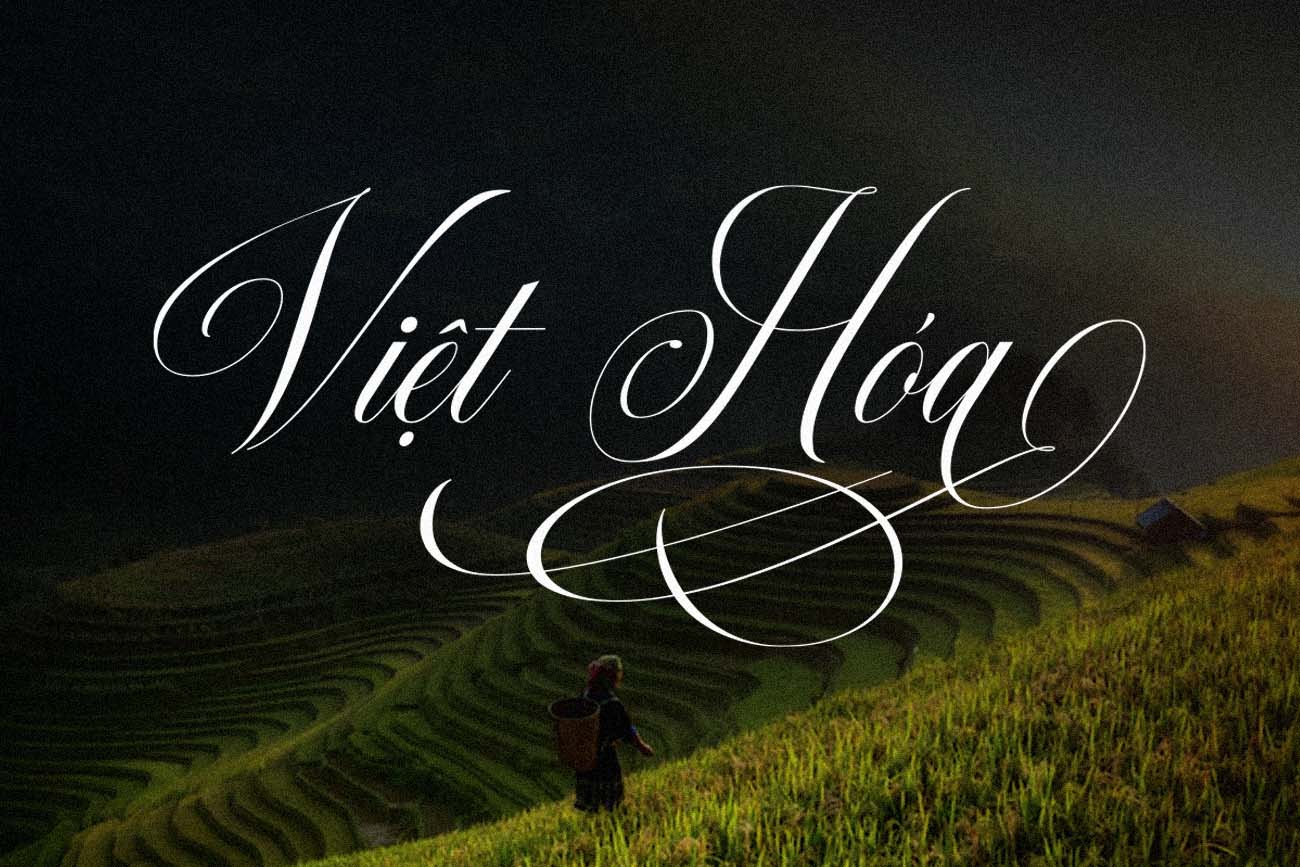
2. TH Newly Bridal – Dịu dàng, lãng mạn
Kiểu chữ có dáng tròn, mềm và hơi nghiêng nhẹ, tạo cảm giác gần gũi và dễ đọc. Các nét được bo đều, không quá sắc nên mang lại sự dễ chịu khi nhìn lâu. Phần đuôi chữ kéo nhẹ tạo điểm nhấn tinh tế mà không bị rối. Tổng thể font mang hơi hướng nữ tính, rất phù hợp cho thiệp cưới, lời chúc hoặc các thiết kế mang màu sắc tình cảm, nhẹ nhàng.
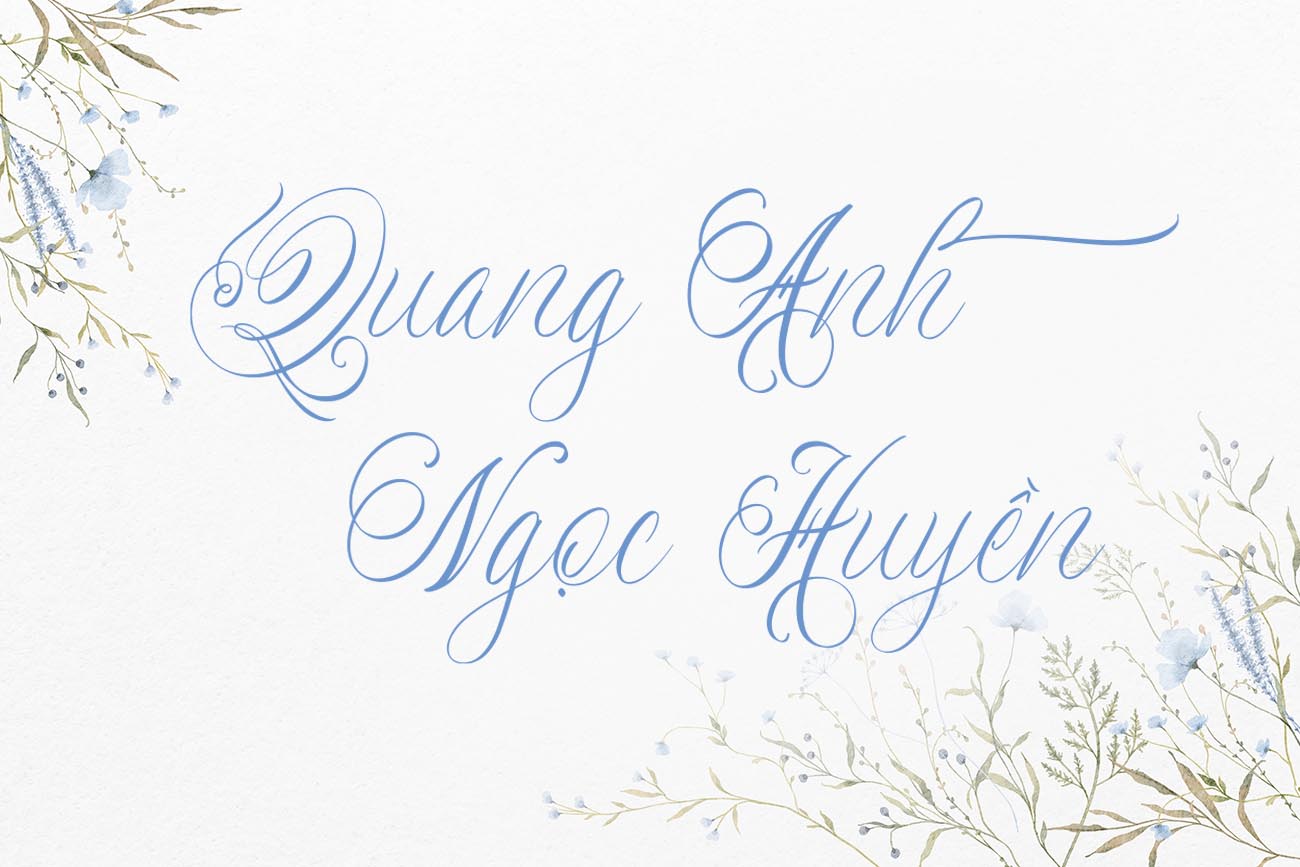
3. TH Berseka – Nghệ thuật, uyển chuyển
Font nổi bật với những đường cong mềm và các chi tiết lượn lớn tạo cảm giác bay bổng. Mỗi ký tự đều có điểm nhấn riêng, đặc biệt ở phần chữ hoa với nét kéo dài rất đẹp. Sự chuyển đổi giữa nét mảnh và nét dày giúp chữ trông sinh động hơn. Kiểu chữ này phù hợp cho tiêu đề trang trí, thiệp cưới hoặc các thiết kế cần tạo ấn tượng ngay từ cái nhìn đầu tiên.
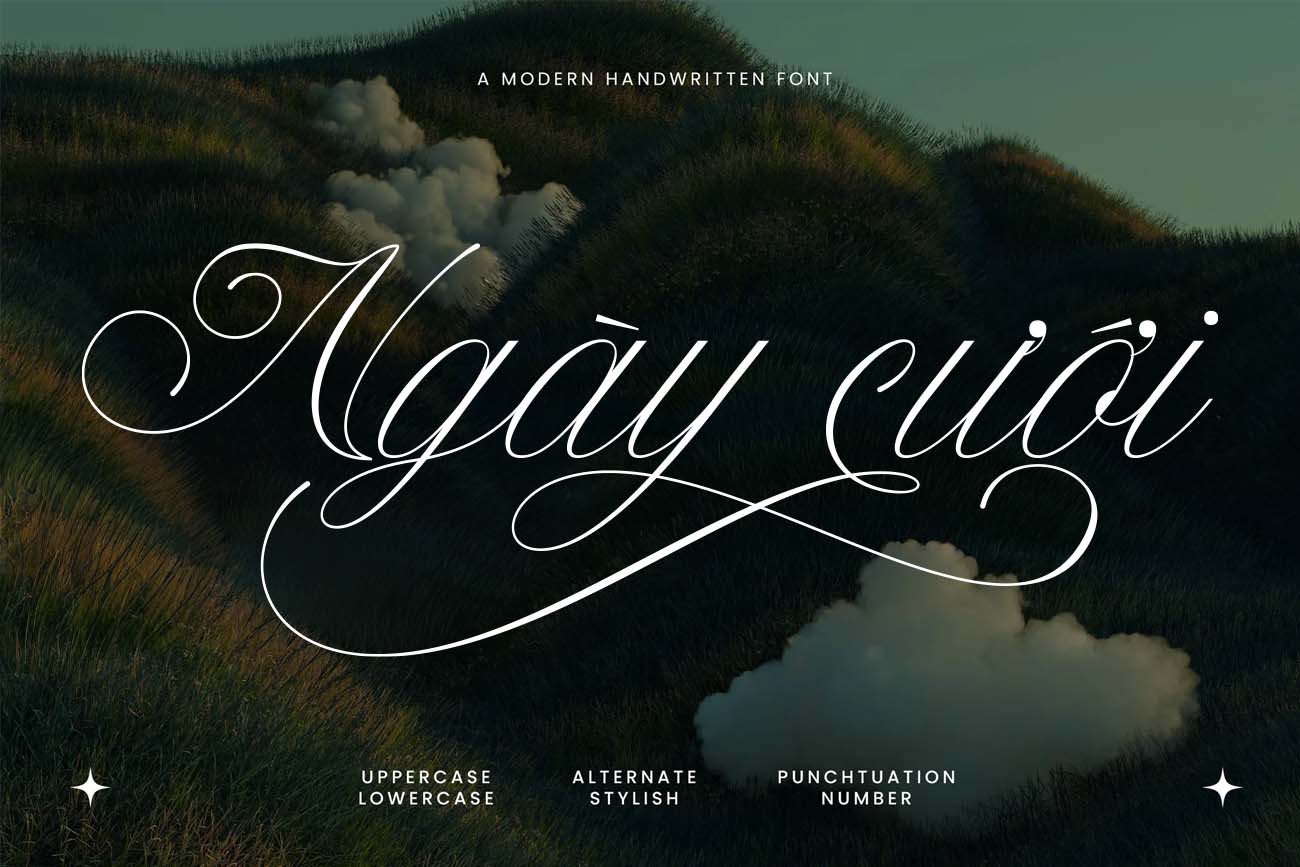
4. TH Jonathan Stattera – Sang trọng, tinh tế
Font mang phong cách chữ ký với các nét liền mạch và thanh thoát. Đường chữ kéo dài tự nhiên, không quá cầu kỳ nhưng vẫn tạo được điểm nhấn. Kiểu dáng chữ hơi nghiêng, tạo cảm giác như chữ ký thật, rất phù hợp với các thiết kế cá nhân hóa. Nhìn tổng thể, font mang lại cảm giác gọn gàng, tinh tế và dễ kết hợp với các kiểu chữ khác trong cùng bố cục.
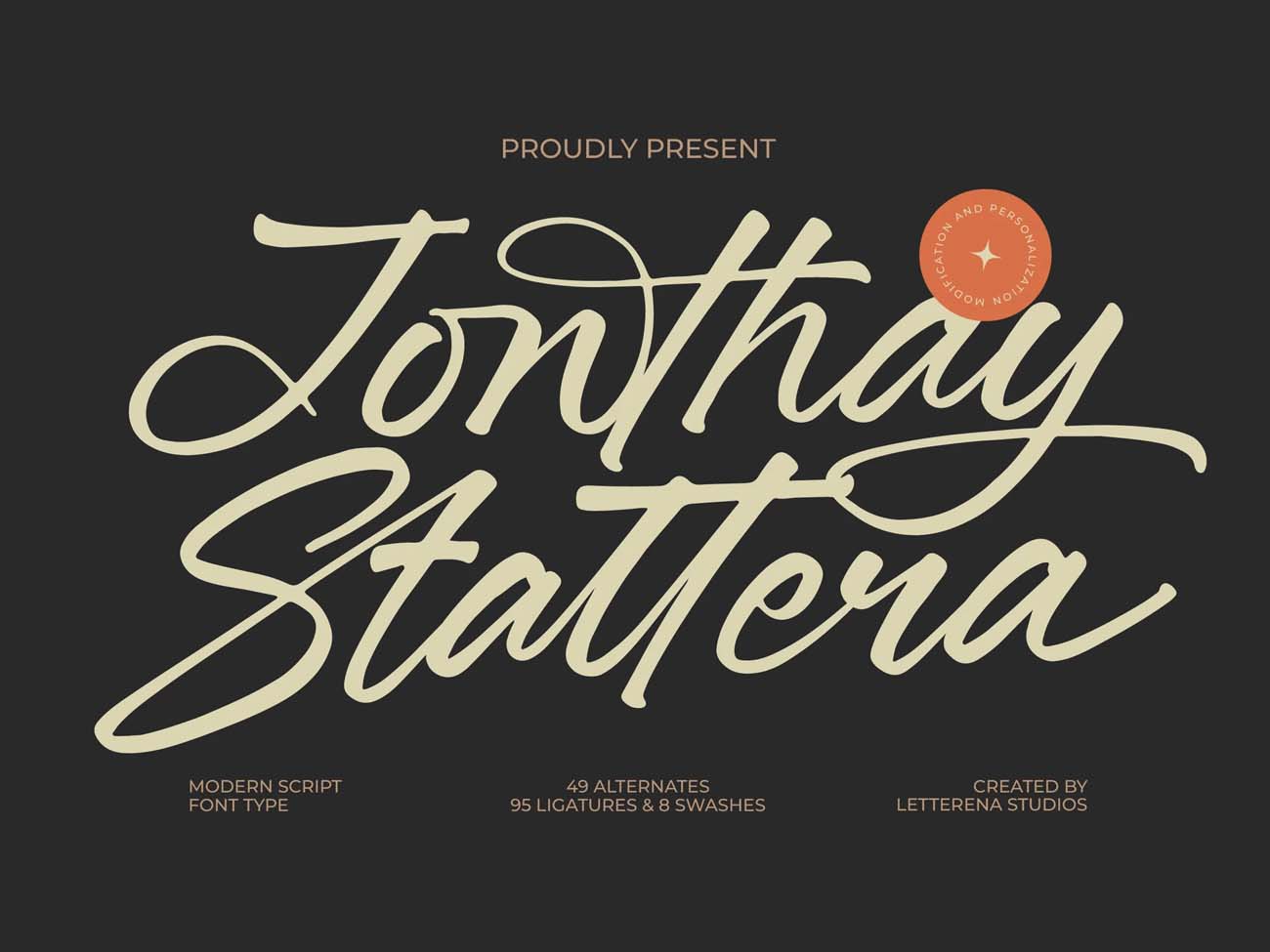
5. TH Ganetha – Mềm mại, thanh thoát
Ganetha có nét chữ nhẹ, uốn cong đều và khá cân đối. Các ký tự được thiết kế không quá phức tạp, giúp dễ sử dụng trong nhiều tình huống. Nét chữ không quá dày nên tạo cảm giác thanh thoát, phù hợp với các thiết kế cần sự nhẹ nhàng. Khi dùng cho tiêu đề hoặc thiệp, font này mang lại cảm giác tinh tế, không bị rối mắt.
📁 Tải xuống font chữ TH Ganetha
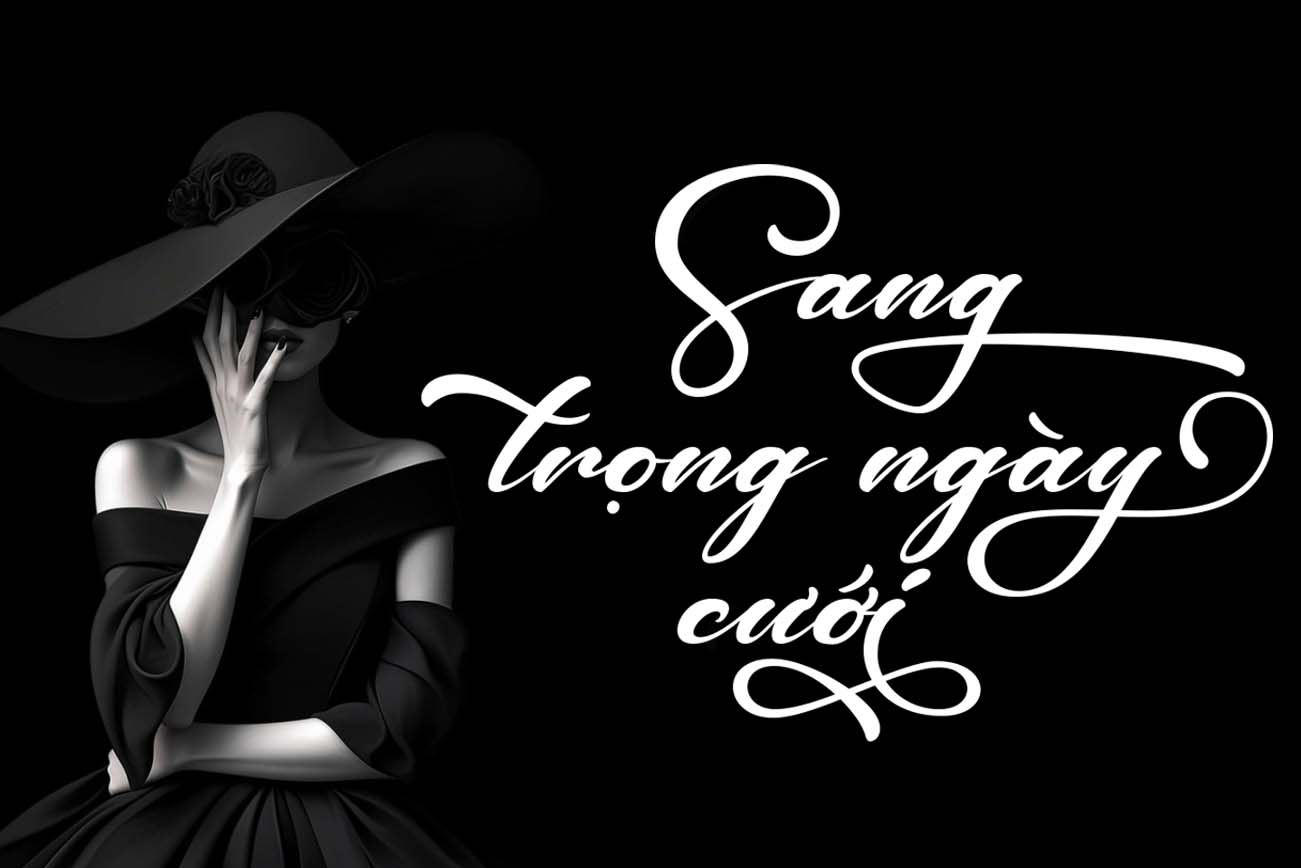
6. TH Bramostia – Cá tính, nổi bật
Font này có nét chữ mạnh, dứt khoát và rõ ràng. Các đường cong được xử lý gọn, tạo cảm giác chắc chắn hơn so với các font mềm mại khác. Dù vẫn giữ phong cách viết tay, nhưng Bramostia thiên về sự cá tính, phù hợp với những thiết kế cần điểm nhấn rõ ràng. Kiểu chữ này rất hợp dùng cho tiêu đề hoặc logo mang phong cách hiện đại.
📁 Tải xuống font chữ TH Bramostia
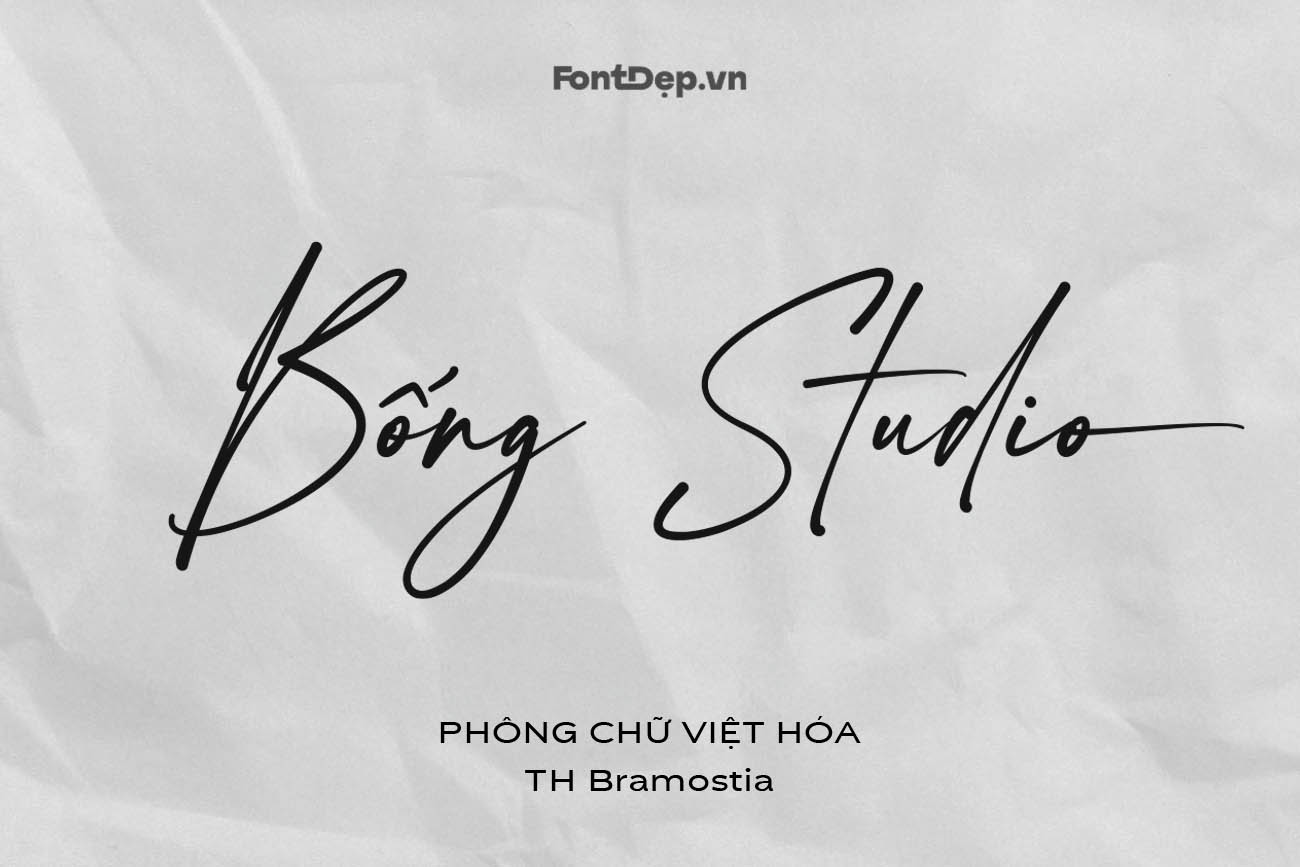
7. TH Kinetic Motion – Mạnh mẽ, hiện đại
Kinetic Motion mang đậm phong cách brush với các nét vẽ dày và có độ chuyển động rõ. Chữ trông như được viết bằng cọ, tạo cảm giác rất sống động. Các nét không đều nhau hoàn toàn, giúp tăng tính tự nhiên. Font này phù hợp với thiết kế quảng cáo, poster hoặc những nội dung cần tạo ấn tượng mạnh ngay từ cái nhìn đầu tiên.
📁 Tải xuống font chữ TH Kinetic Motion
![[Tải Về] Font Brush TH Kinetic Motion Việt Hóa – Nét Cọ Mạnh Mẽ & Hiện Đại](https://fontdep.vn/storage/font-images/font%20chu%20brush%20TH%20Kinetic%20Motion%20viet%20hoa%20anh%201-20250703-130122.jpg)
8. TH Viettay 7 – Phóng khoáng, linh hoạt
Font có nét uốn lượn rõ ràng, mang cảm giác thoải mái và tự nhiên. Các ký tự được thiết kế không quá khuôn mẫu, tạo nên sự mềm mại và linh hoạt. Nét chữ có độ dày vừa phải, đủ để nổi bật mà không gây nặng mắt. Kiểu chữ này dễ dùng trong nhiều thiết kế khác nhau, từ banner đến nội dung mạng xã hội.
📁 Tải xuống font chữ TH Viettay 7
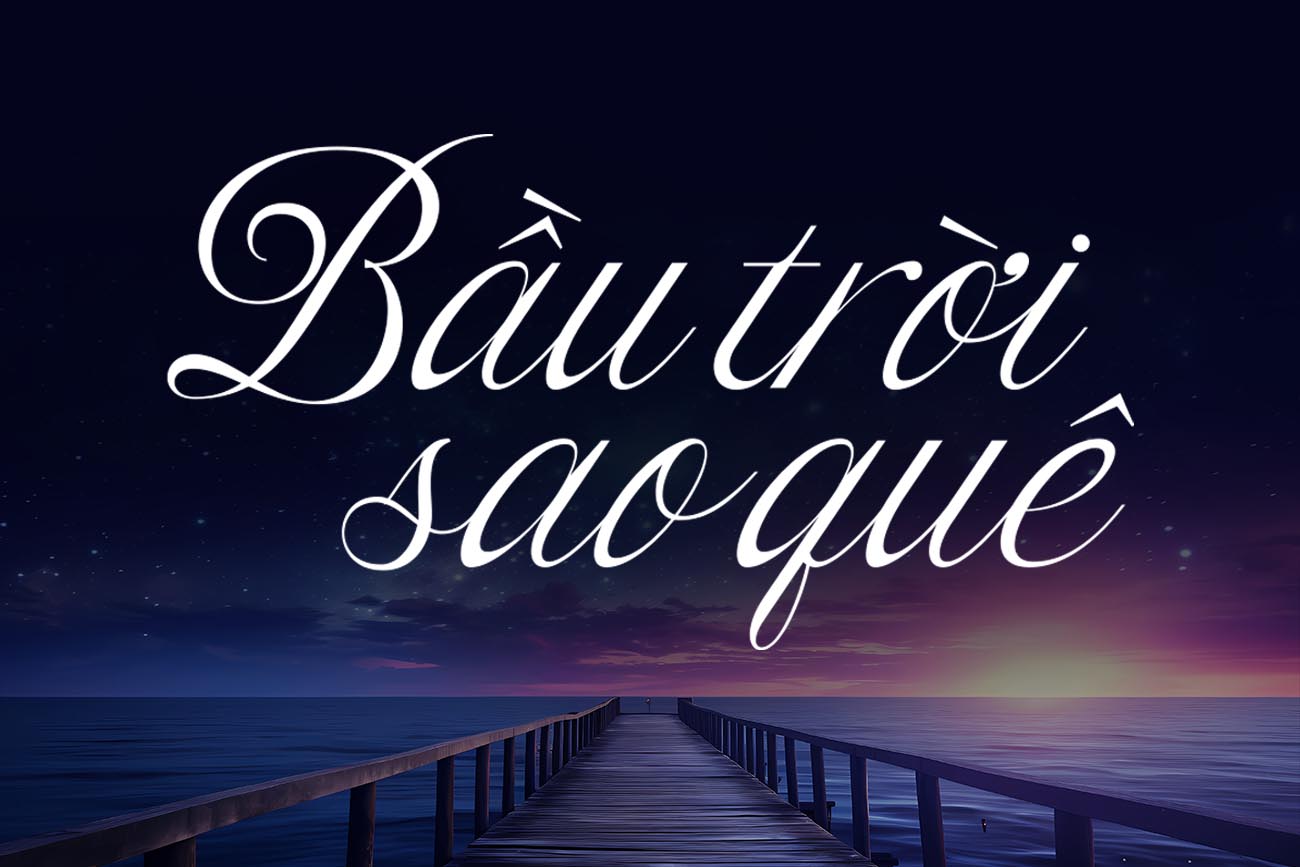
9. TH Mrattoos Regular – Gọn gàng, hiện đại
Font mang phong cách chữ ký đơn giản nhưng hiệu quả. Các nét chữ không quá cầu kỳ, được giữ ở mức vừa phải để đảm bảo dễ đọc. Kiểu dáng chữ khá đều, giúp tạo cảm giác gọn gàng và chuyên nghiệp. Font này phù hợp cho logo cá nhân hoặc các thiết kế cần sự tinh giản.
📁 Tải xuống font chữ TH Mrattoos
![[Tải về] Font chữ ký viết tay đẹp TH Mrattoos Regular Việt hóa hoàn chỉnh](https://fontdep.vn/storage/font-images/01JWBKWES1CD36MACF5TNR1C14.jpg)
10. TH Bengoda – Nhẹ nhàng, thanh lịch
Bengoda có nét chữ mảnh, uốn cong nhẹ và rất dễ nhìn. Các ký tự được thiết kế cân đối, không bị quá bay nên giữ được sự ổn định. Font mang lại cảm giác nhẹ nhàng, phù hợp với các thiết kế mang tính nữ tính hoặc tinh tế. Khi dùng làm tiêu đề, chữ vẫn giữ được sự rõ ràng.
📁 Tải xuống font chữ TH Bengoda
-20250815-090501.jpg)
11. TH Histerm – Tinh tế, mềm mại
Font này nổi bật với các nét chữ uyển chuyển và có độ cong vừa phải. Các ký tự được nối với nhau khá tự nhiên, tạo cảm giác liền mạch. Kiểu chữ không quá phức tạp nên dễ ứng dụng trong nhiều thiết kế. Tổng thể mang lại cảm giác tinh tế, phù hợp với thiệp hoặc nội dung mang tính trang trọng.
📁 Tải xuống font chữ TH Histerm
-20250815-091054.jpg)
12. TH Maddison Signature – Thanh thoát, hiện đại
Font mang phong cách chữ ký với nét mảnh và dài. Các ký tự được kéo nhẹ ở phần cuối, tạo điểm nhấn nhưng không gây rối. Kiểu chữ này tạo cảm giác hiện đại và cá nhân hóa cao. Khi dùng cho logo hoặc chữ ký thương hiệu, font giúp tăng độ nhận diện khá tốt.
📁 Tải xuống font chữ TH Maddison Signature
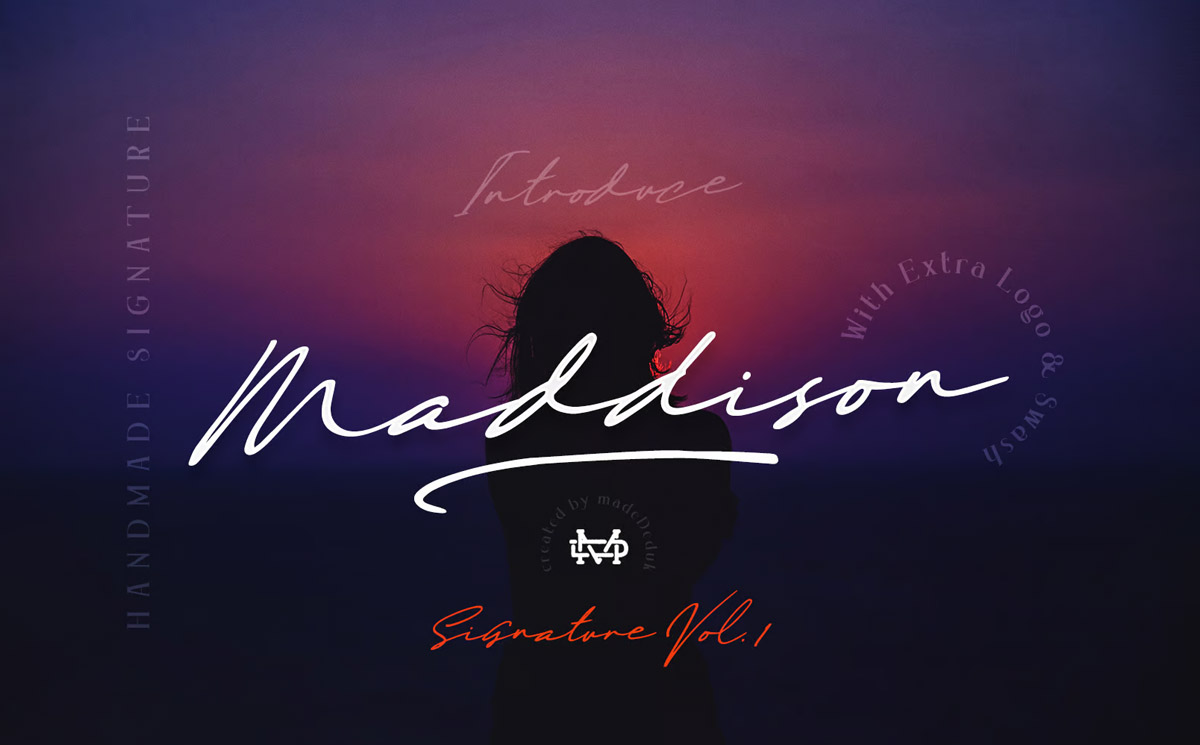
13. TH Maistoray – Tự nhiên, cuốn hút
Font có nét chữ mềm, không quá đều, tạo cảm giác rất giống chữ viết tay thật. Các đường cong nhẹ nhàng giúp chữ trông gần gũi hơn. Kiểu chữ này phù hợp với những thiết kế cần sự tự nhiên, không quá cầu kỳ nhưng vẫn có điểm nhấn riêng.
📁 Tải xuống font chữ TH Maistoray
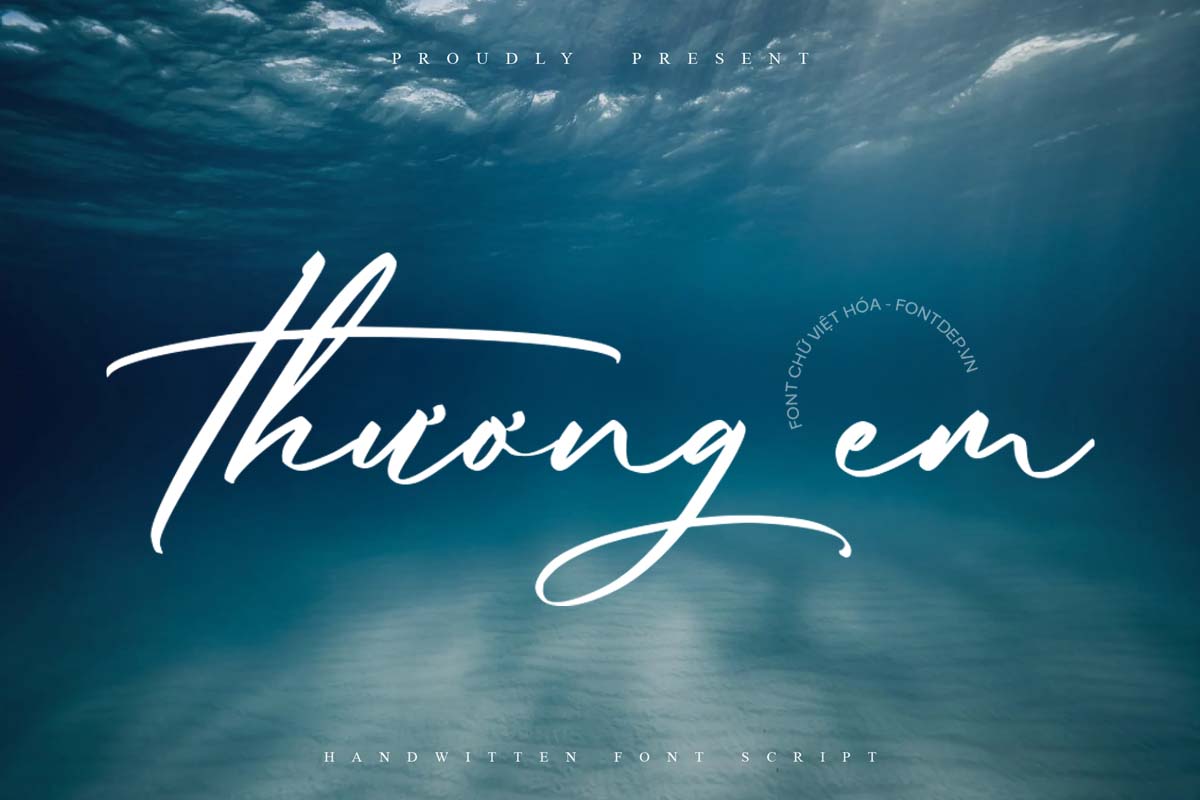
14. TH Maryatha – Cổ điển, dịu dàng
Maryatha mang phong cách vintage với các nét chữ mềm và hơi uốn cong. Các ký tự có sự cân đối tốt, tạo cảm giác hài hòa khi nhìn tổng thể. Font này phù hợp với các thiết kế mang hơi hướng cổ điển, nhẹ nhàng và có chút hoài niệm.
📁 Tải xuống font chữ Maryatha
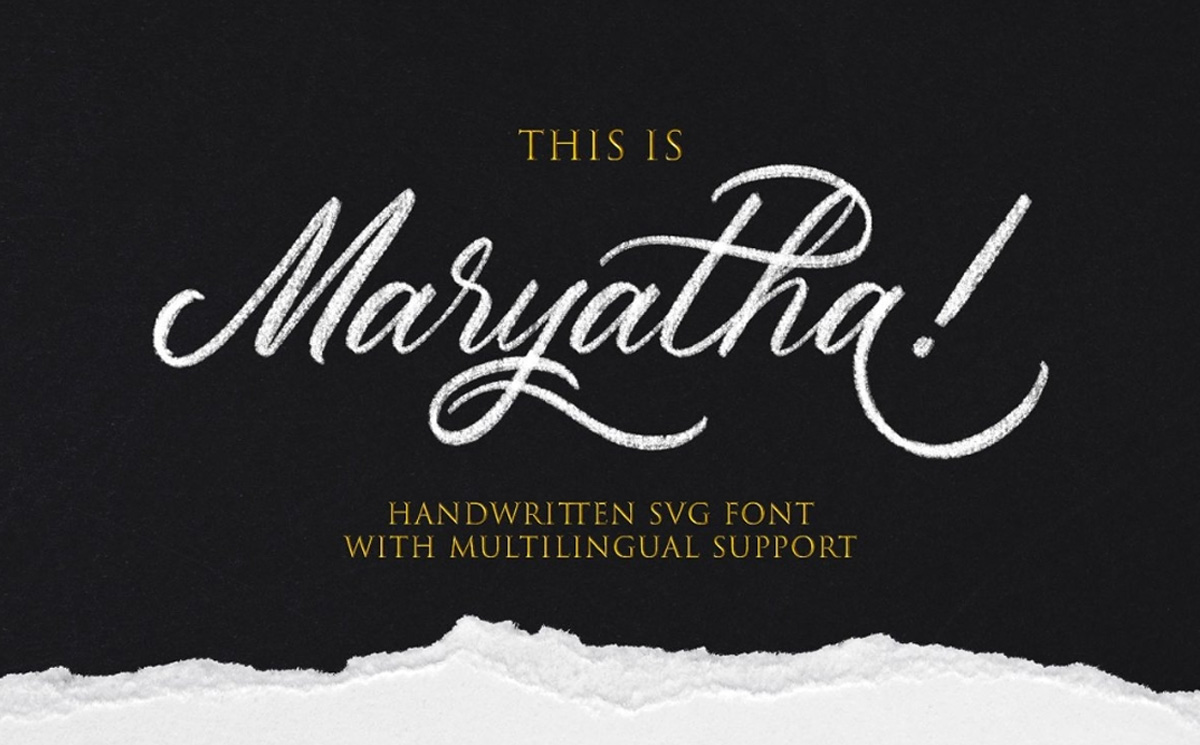
15. TH Milyah – Thanh thoát, sang trọng
Font mang phong cách chữ ký với nét mảnh, dài và hơi nghiêng, tạo cảm giác tinh tế và hiện đại. Các ký tự được nối liền nhẹ nhàng, phần đuôi kéo dài giúp chữ có điểm nhấn nhưng vẫn giữ được sự gọn gàng. Khi sử dụng, font tạo cảm giác cá nhân hóa khá rõ, phù hợp với logo, watermark hoặc thương hiệu cá nhân. Phù hợp cho logo và chữ ký, không nên dùng cho đoạn văn dài vì nét chữ khá mảnh.
📁 Tải xuống font chữ TH Milyah
Cách cài đặt font chữ viết tay trên máy tính và Canva đơn giản, dễ làm
Sau khi tải font chữ viết tay về máy, bạn chỉ cần thực hiện vài bước đơn giản là có thể sử dụng ngay trong thiết kế. Dưới đây là hướng dẫn cài đặt font trên các nền tảng phổ biến:
Cài đặt font trên Windows
- Giải nén file font (thường là .zip)
- Mở file có định dạng .ttf hoặc .otf
- Nhấn Install (Cài đặt) để hoàn tất
Sau khi cài xong, font sẽ tự động xuất hiện trong Word, Photoshop, Canva…
Cài đặt font trên Mac
- Mở ứng dụng Font Book trên máy
- Chọn Add Font
- Tải file font vừa tải về lên
Font sẽ được lưu và sẵn sàng sử dụng trong các phần mềm thiết kế.
Sử dụng font trên Canva
- Vào mục Upload a font (tải font lên) trong Canva (áp dụng với tài khoản Canva Pro)
- Chọn file font từ máy tính
- Hoặc sử dụng các font viết tay có sẵn trong thư viện Canva
Việc tải font lên Canva giúp bạn đồng bộ thiết kế và sử dụng linh hoạt hơn.
Xu hướng font chữ viết tay 2026
- Tối giản (minimal handwritten)
- Cá nhân hóa thương hiệu
- Kết hợp AI & typography
Giải đáp nhanh (FAQ)
Font viết tay có dùng cho logo được không?
→ Có, nhưng nên chọn font rõ nét, không quá rối.
Font viết tay Việt hóa là gì?
→ Là font có hỗ trợ đầy đủ dấu tiếng Việt.
Có bao nhiêu loại font viết tay?
→ Thường chia thành: signature, casual, brush, calligraphy.
Font viết tay và serif nên dùng loại nào?
→ Viết tay dùng cho cảm xúc, serif dùng cho nội dung dài.
Font chữ viết tay không chỉ giúp thiết kế đẹp hơn mà còn mang lại cảm xúc riêng cho từng nội dung. Chỉ cần chọn đúng kiểu chữ và sử dụng hợp lý, một thiết kế đơn giản cũng có thể trở nên thu hút và có điểm nhấn rõ ràng.